このシリーズでは、文字・書体に関する展示を紹介していきます。 初回は、2025年9月30日〜11月28日に慶應義塾ミュージアム・コモンズで開催されていた『慶應義塾ミュージアム・コモンズ×飯沼観音圓福寺 嵯峨本の誘惑:豪華活字本にみた夢』です(展覧会は現在終了しています)。
嵯峨本は、江戸時代初期に光悦流の筆跡による流麗な連綿体の木活字で印刷され、美しい料紙や装丁を特徴とした活字本で、その名称は刊行場所、京都の嵯峨にちなみます。現在では角倉素庵が主体となって製作されたものと認識されているそうです。
嵯峨本は一つの作品に複数のバーションが存在する場合もあり、この展示ではそれらを比較して見ることができる貴重な機会でした。
『伊勢物語』の同内容のページが数冊並べて展示されているセクションでは版の違いが確認できました。本文の内容は同じでも、文字を入れ替えて別の活字に変更しており、とても手間のかかる作業をしていることが窺えました。
単なるあそび…?と頭を捻りましたが、これらは世の中に1つしかない写本に近づける行為の一つとして挙げられており、読者が気づくか分からないこだわりも、意味の込められたものでした。一枚の版木ではできない、活字によって一部の文字の組み替えが可能になっている点は、私が作っているフォントでは当たり前になっていて思いがけず繋がる部分で、感慨深かったです。
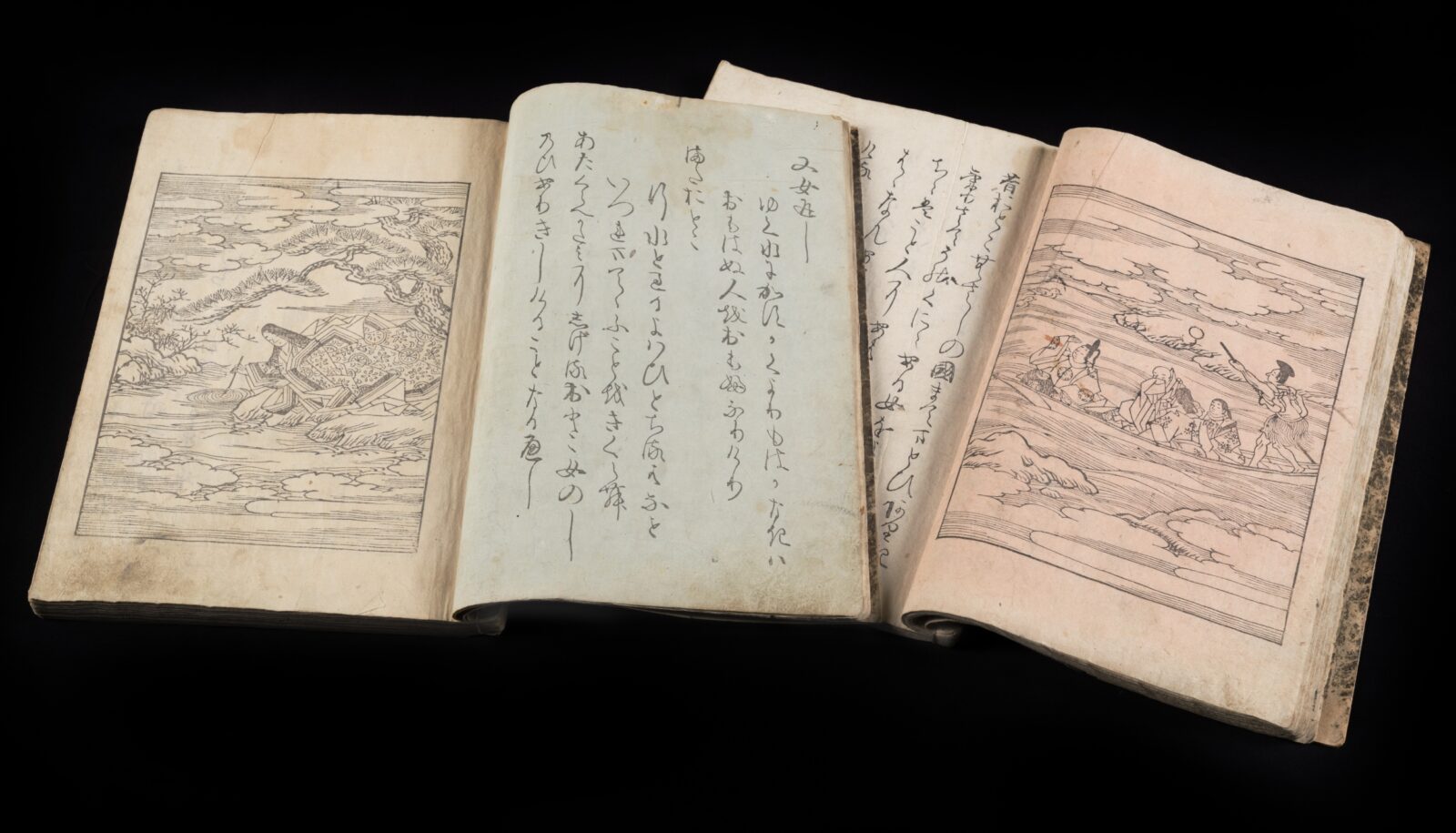
行間や版面の天地左右のアキ、刷りの綺麗さから、リズムに富んだ流麗な連綿の文字を読みやすくする工夫が見えて、作業の精巧さに驚きました。どのようにこの活字が彫られたのか、誰の文字なのか疑問は尽きず、謎の多い嵯峨本に惹きつけられました。
[2](左)『伊勢物語』〔慶長13年(1608)〕刊、嵯峨本第2種本、2巻存上1冊(右)『伊勢物語』〔元和寛永頃〕刊、2巻2冊、飯沼観音圓福寺蔵
[3]『伊勢物語』慶長13年(1608)刊、嵯峨本第1種本、2巻2冊、相応院旧蔵、飯沼観音圓福寺蔵